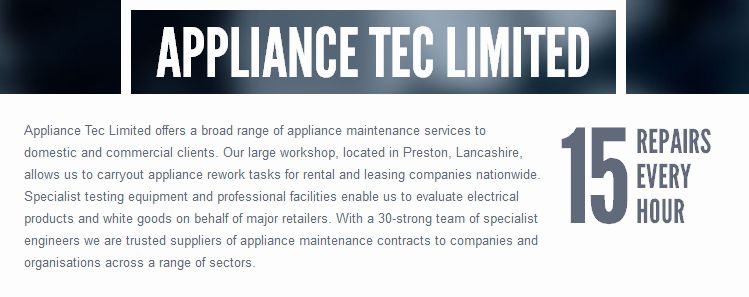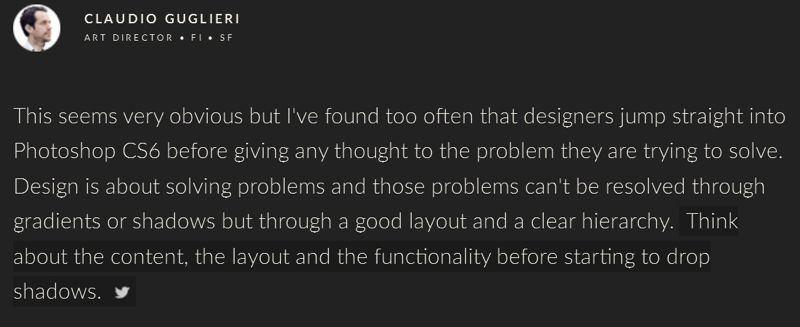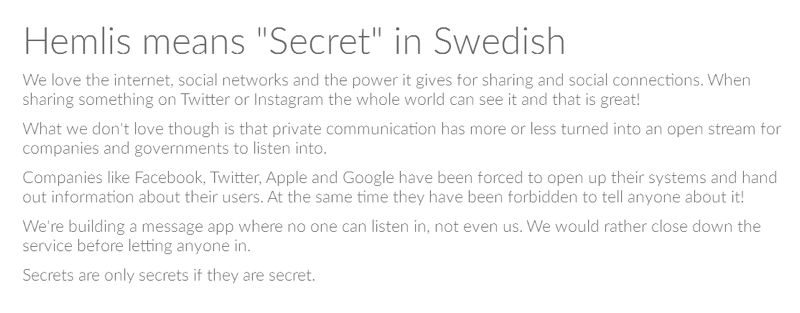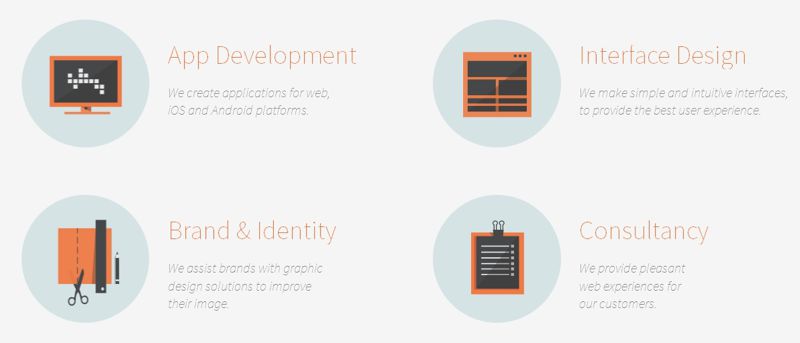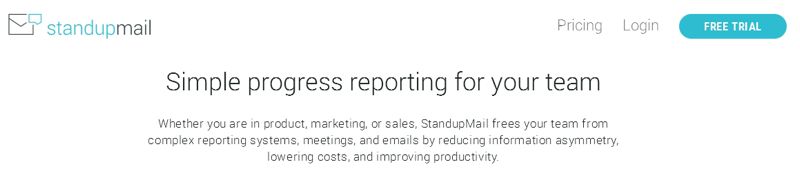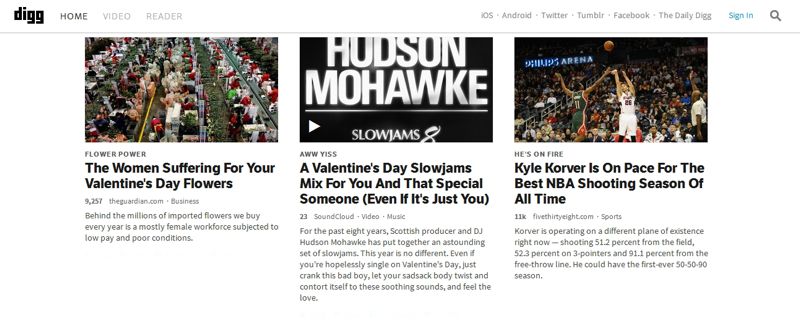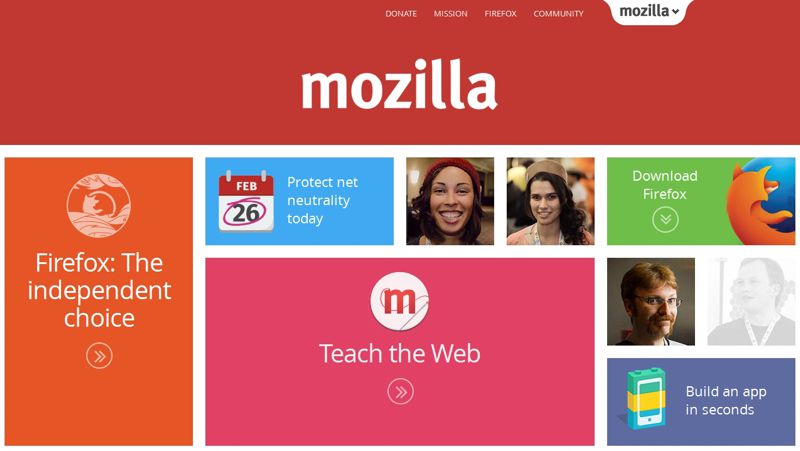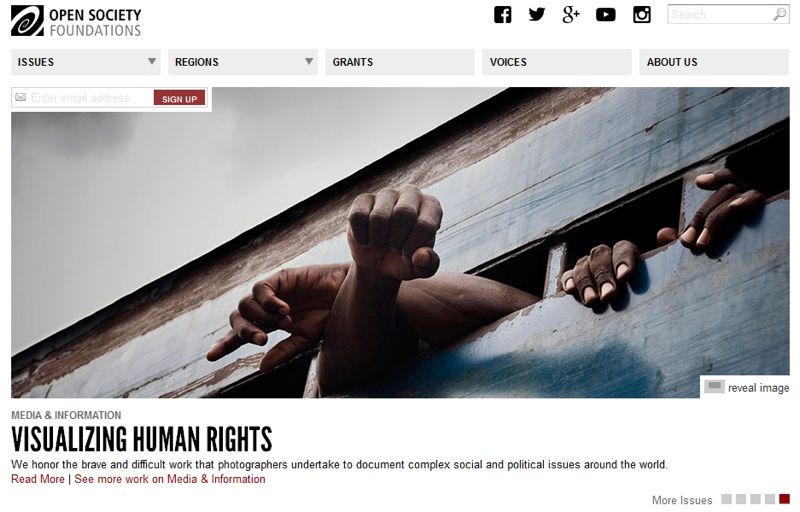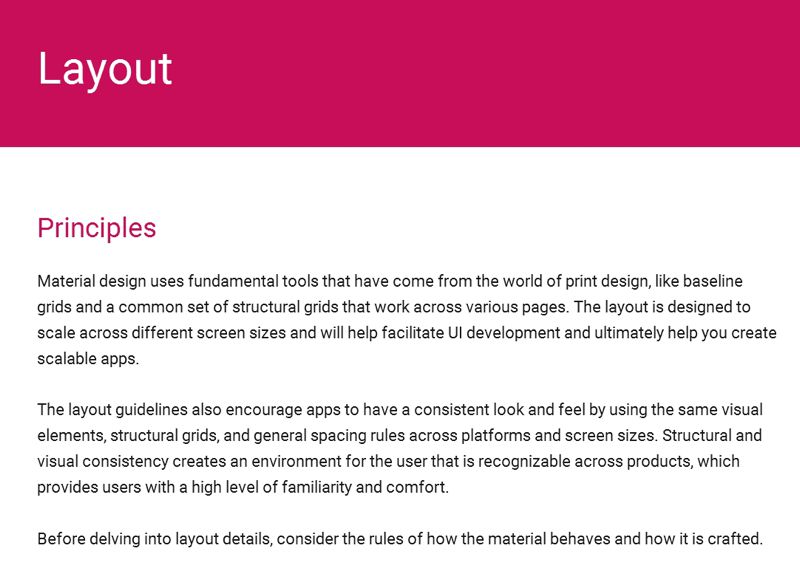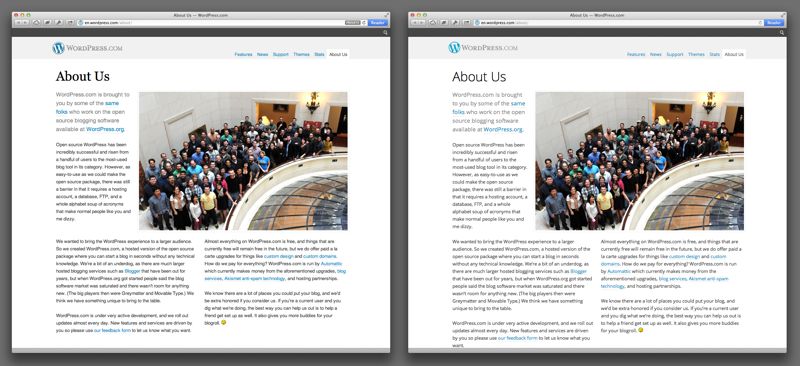
Tải miễn phí 5 font chữ cao cấp cho thiết kế web hoàn hảo
Hôm nay chúng tôi sẽ mang tới một số lựa chọn font chữ miễn phí nhưng chất lượng lại đặc biệt cao cấp để bạn tạo được thiết kế website đẹp của riêng mình mà không tốn nhiều chi phí.
Tìm được font chữ phù hợp cho thiết kế web chuyện nghiệp là một thử thách cả với những chuyên gia thiết kế đầy kinh nghiệm. Điều này còn khó hơn nếu sự lựa chọn của bạn chỉ có thể gói gọn trong các font chữ miễn phí để tiết kiệm tối đa chi phí.
Hôm nay chúng tôi sẽ mang tới một số lựa chọn font chữ miễn phí nhưng chất lượng lại đặc biệt cao cấp để bạn tạo được thiết kế website đẹp của riêng mình mà không tốn nhiều chi phí.
Open Sans
Open Sans được sử dụng rộng rãi kể từ khi được Google giới thiệu năm 2011. Nó được thiết kê bởi Steve Matteson và có nhiều điểm chung với Droid Sans, ngoại trừ việc nó có kiểu in nghiêng và độ rộng chứ lớn hơn.
Với 897 ký tự đầy đủ, bạn sẽ làm được mọi việc với font chữ này. Có 5 kích thước khác nhau cho bạn chọn: 300 Light, 400 Normal, Semi-Bold 600, Bold 700 và Extra Bold 800 và cũng tầng đó lựa chọn với kiểu in nghiêng.
Thêm vào đó, Open Sans Condensed font có sẵn cho 3 mục đích : in ấn, web, di động. i
Open Sans đã được sử dụng rộng rãi trong các bản in của Google và quảng cáo trên website. Hãy xem cách dùng font chữ này trên Google Maps.
Ngoài ra, WordPress.com cũng đã chuyển sang dùng Open Sans vào tháng October 2012, sau khi sử dụng nó vào hệ thống WordPress.org Content Management.
Tương tự như WordPress,Mozilla cũng tận dụng Open Sans và bạn có thấy sự xuất hiện của font chữ ấy ở mọi ngóc ngách của trình duyệt web này.
League Gothic
League Gothic mang hơi hướng cổ điển bởi nó lấy cảm hứng từ Al-ternate Gothic #1, nguyên tác bởi Morris Fuller Benton năm 1903. Giờ đây kiểu chữ này đã trở nên quá phổ biến.
League Gothic được cấp bản quyền miễn phí cho người dùng. Hãy cùng xem một thiết kế website ấn tượng nhờ sử dụng hợp lý font chữ này. League Gothic được dùng ở header, mang lại sự thanh lịch cho trang web.
Thiết kế website công ty Appliance Tec Ltd. là một thiết kế đơn trang nơi mà League Gothic phát huy tối đa ưu điểm của mình.
Roboto
Roboto có sự thành công hơđièu Droid Sans (hệ thống font cho hệ điều hành Google Android) Nó cùng miễn phí cho bạn tải về.
Bạn sẽ sở hữu các phong cách chữ từ mỏng, trung bình đến đậm. Cùng với Open Sans, Roboto là một thành công mà Google mang đến cho cộng đồng. Hãy xem ví dụ của Material Design Styleguide:
Roboto khá hợp với các thiết kế web đơn trang. Đây là một minh chứng với StandupMail:
Lato
Lato là kiểu chữ sans serif family được thiết kế mùa hè 2010 bởi nhà thiết kế Łukasz Dziedzic . Nó hỗ trợ hơn 100 ngôn ngữ Latin , 50+ ngôn ngữ Cyrilliccũng như Hy Lạp và từ ngữ IPA.
Ví dụ tuyệt vời nhất của Lato là trang Frank Chimero's "What Screens Want". Trong trường hợp này, Lato đã đóng góp công lớn trong việc kể câu chuyện trên website.
Một website thú vị khác mà Lato phát huy hiệu quả là Designer checklist advices.
Landing page của Hemlis sử dụng Lato như là font chữ chính.
Source Sans Pro
Cũng là một sans-serif typeface, Source Sans Pro được tạo ra bởi Paul D. Hunt dành cho Adobe. Nó là nguồn dont mở đầu tiên từ Adobe.
Source Sans Pro có 6 kích thước: Regular, ExtraLight, Light, Semibold, Bold, Black. Kiểu chữ này hỗ trợ nhiều ngôn ngữ: Latin script, bao gồm Tây và Tây Âu, Việt Nam, Trung Quốc và Navajo.
digg sử dụng Source Sans Pro như là font chữ chính.
Scytale cũng sử dụng Source Sans như font chữ chính của website.